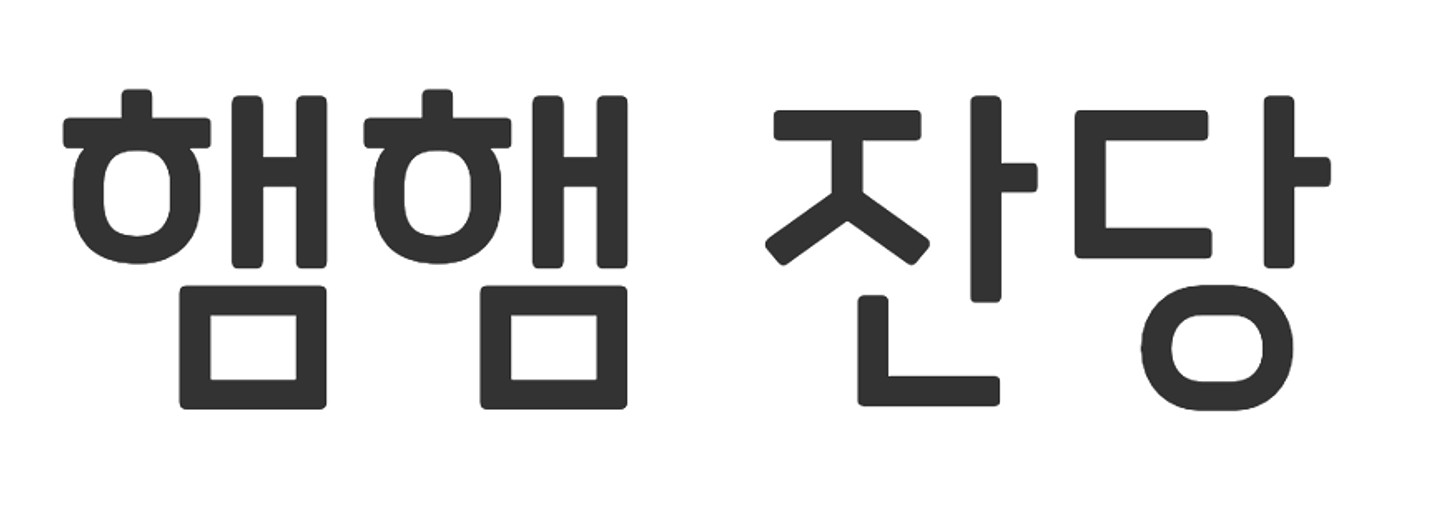
이거무슨폰트인가여
설화수 영문폰트 궁금합니다. 인스타그램에 쓰는 폰트요
쇼츠 자막인데 무슨 폰트일까용??
태도에 관하여 - 임경선 책인데요 이 폰트는 뭐인지 알 수 있을까요?!
폰트 질문 드립니다 출처 : 네이버 홈에 떠서 봤습니더.
메뉴에 사용된 폰트를 알고 싶어요 어떤분은 a고운글씨M 이라고 하시는데... 폰트 모양이 조금 다른거같아 문의 드립니다
현대산업차량 홈페이지에서 캡쳐했고 산돌에서 찾아도 안나와서 물어봅니다 어떤폰트일까요?
무슨 폰트인지 궁금해요. 이미지로 폰트 검색해도 안 나오네요ㅠ 아시는 분 알려주시면 감사하겠습니다..!
이 폰트 뭘까유ㅠ
이거 뭔가요?
HG꼬딕씨 << 아니에요ㅜ 꼬딕씨라고 답변 달지마세용 분홍색 박스에 들어가있는 폰트 뭔지 아시는 분 있나요? 처음에는 꼬딕씨인줄 알았는데 적어보니까 ㅍ,ㅋ,ㅅ 모양들도 다르고 영어 폰트도 다르네여 ㅠㅠ